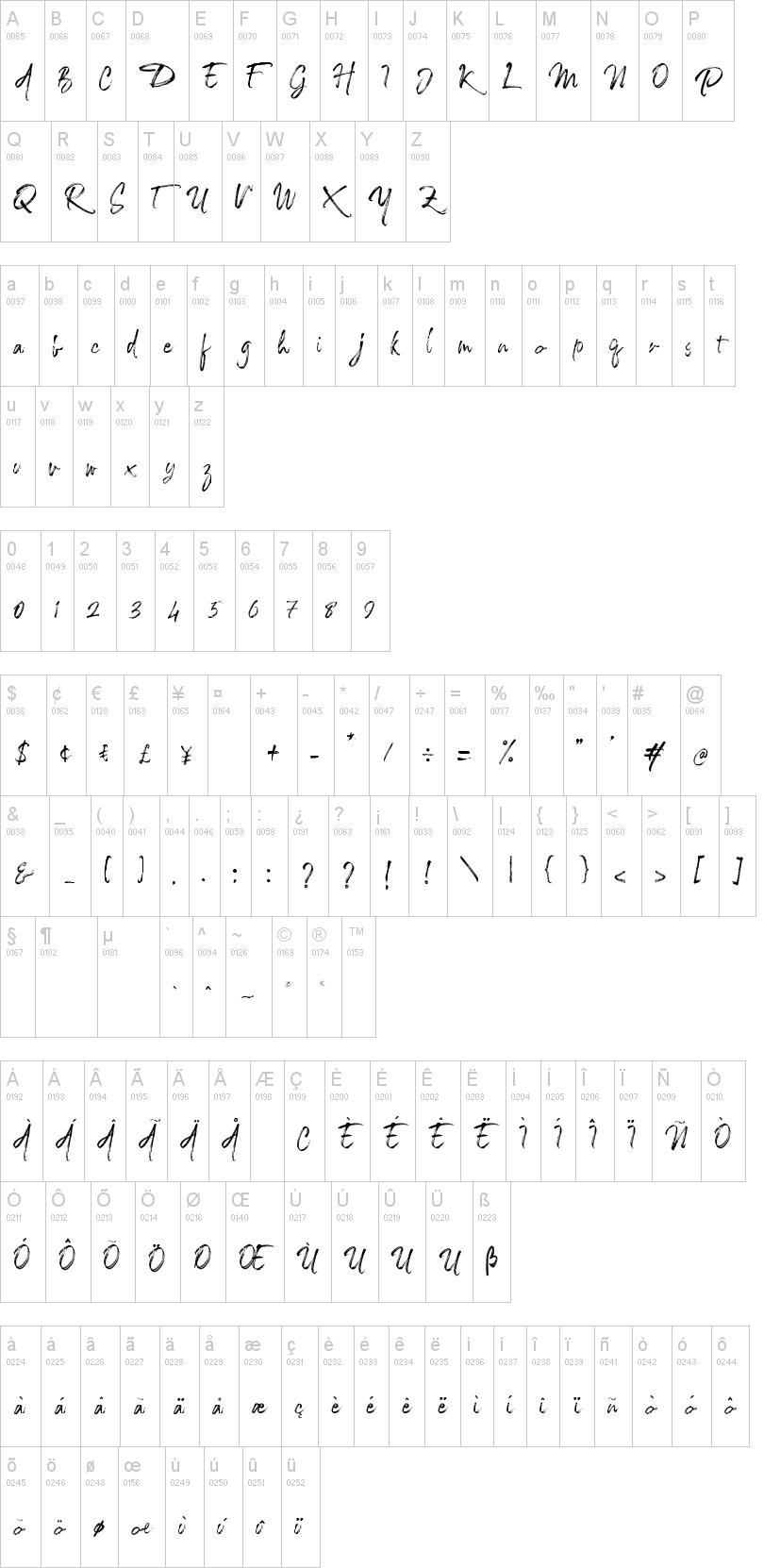
The Caldwell Script
The Caldwell Script是一款英文手写体字体,由英国设计师Caldwell绘制。它的字体风格以细腻的线条和温柔的角度为特色,营造出一种温馨、优雅的氛围。此外,The Caldwell Script字体也拥有优秀的可读性,可以有效地传达设计者的信息,同时也为文字添加了特殊的艺术气息。
The Caldwell Script是一款非常不错的手写艺术字体,具有很好的视觉感,适合于文化类的宣传设计、商业类品牌的广告和产品包装设计以及个性化文字排版等较多场景。
The Caldwell Script字符映射图